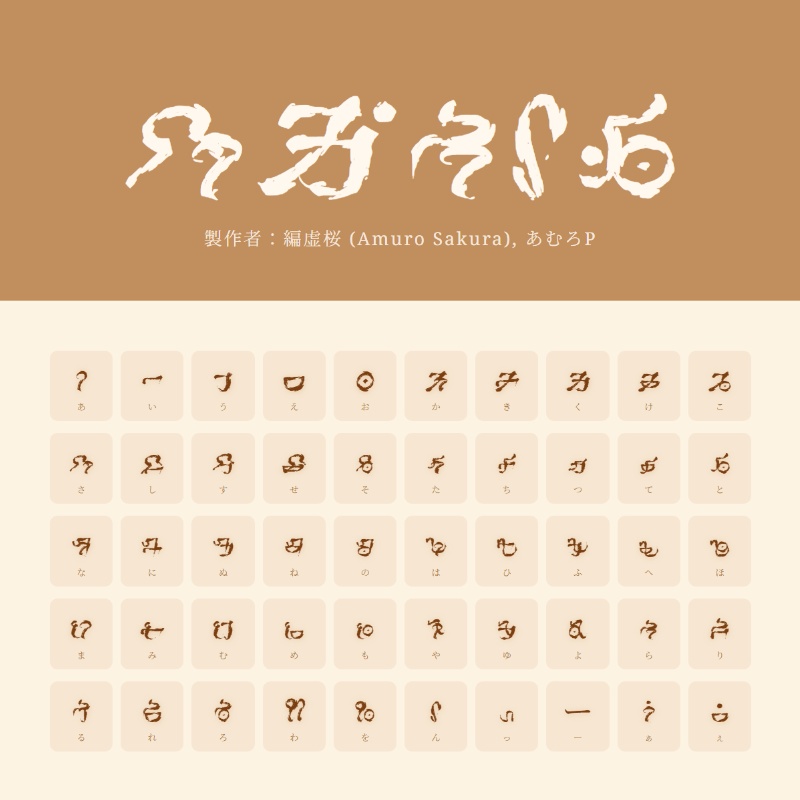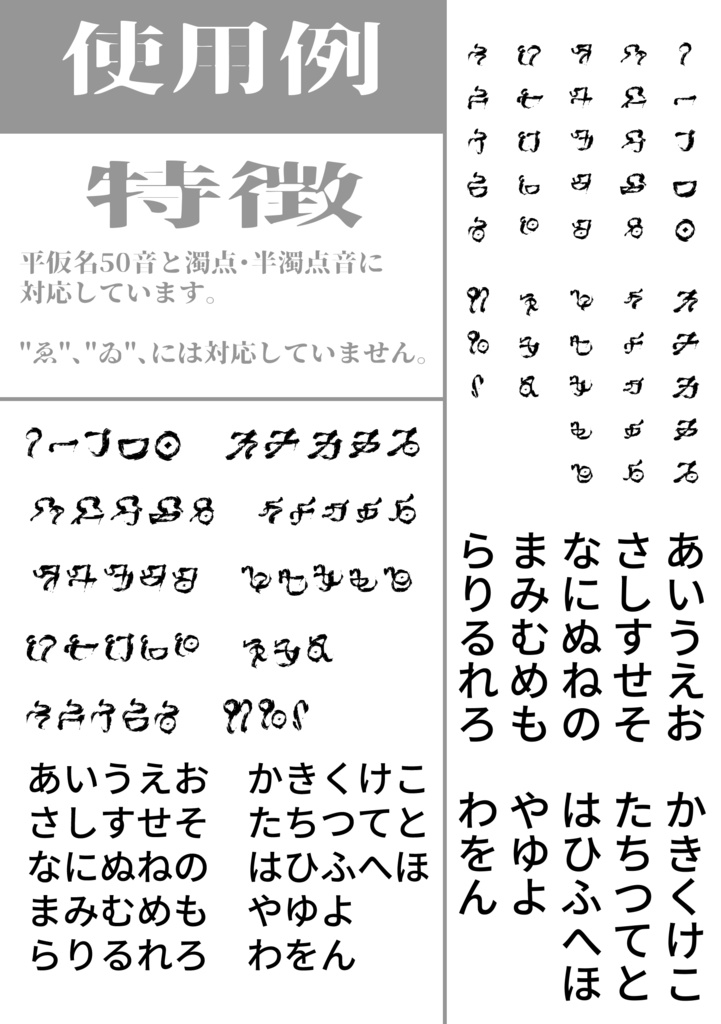
異世界風フォント「さぐらんど」
ひらがなを打つだけで異世界文字になるふぉんと、「さぐらんど」 ■ 製品の特長 ・ ひらがな入力だけで簡単実装 ・ マンガ・ゲーム・動画制作の商用利用に対応 ■コンセプト ファンタジーを意識して制作しました。 ※文字には規則性があります!ぜひ考えてみてください! ■ 製品の特長 ・ ひらがな入力だけで簡単実装 ・ マンガ・ゲーム・動画制作の商用利用に対応 ■ こんな用途におすすめ ・建物の看板 ・ ファンタジー世界の地図、看板、石碑の文字 ・ ゲームのUI、ステータス画面、アイテム説明 ・ 神託や古代文書の文字 ■ 収録内容・製品仕様 ・収録文字:ひらがな50音 / 濁音 / 半濁音 ・ 非対応文字:ゐ / ゑ / 漢字 / カタカナ /英数字 ・ ファイル形式:OpenTypeフォント (.otf) (※ZIP形式で圧縮されていますので、解凍してご利用ください) ■製作者:あむろP, 編虚桜 ■ ご利用規約 ご購入前に必ずご確認ください。フォントの購入者は、本規約に同意したものとみなします。 ・商用利用可能です。ゲーム、動画、書籍、グッズなどでの利用が可能です ・個人利用・同人活動可能です。趣味のイラスト、同人誌、Webサイトなど ・フォントの改変、文字の変形、デザインの変更は禁止です ・フォントの再配布・販売、フォントファイル自体の譲渡・販売は禁止です ・返品は受け付けておりません。ご了承ください。